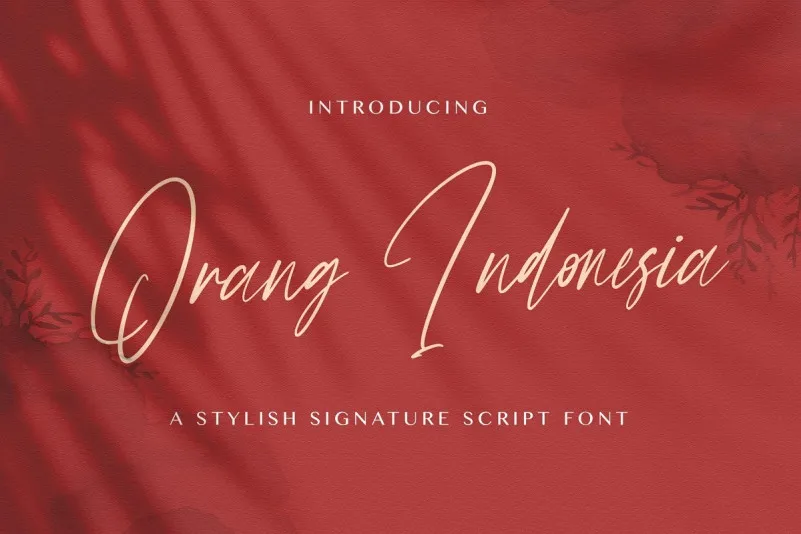
A fonte ‘Orang Indonesia Font’ é uma elegante escolha para quem busca personalidade em seus projetos de design. Ela traz a autenticidade única do traço humano a sua lista infinita de ideias criativas, desde logotipos e assinaturas até embalagens e headlines de blogs. Com os caracteres bem equilibrados e um estilo único, a Orang Indonesia é uma opção perfeita para aqueles que buscam se destacar em seus designes. É fácil incorporar este traço natural à sua arte digital, proporcionando resultados vibrantes e inovadores. Que tal dar vida a suas ideias mais audaciosas? O ‘Orang Indonesia Font’ está pronto para torná-las uma realidade visível.